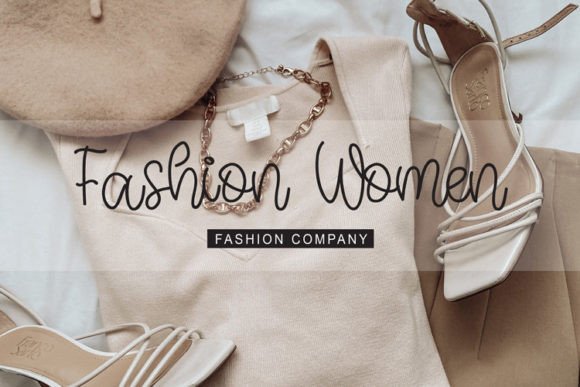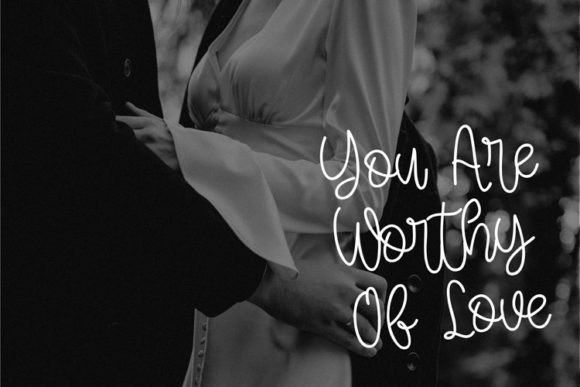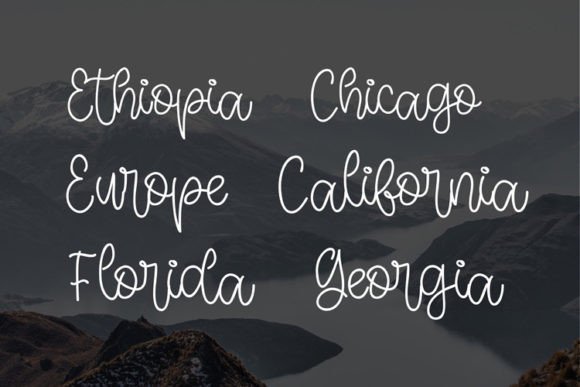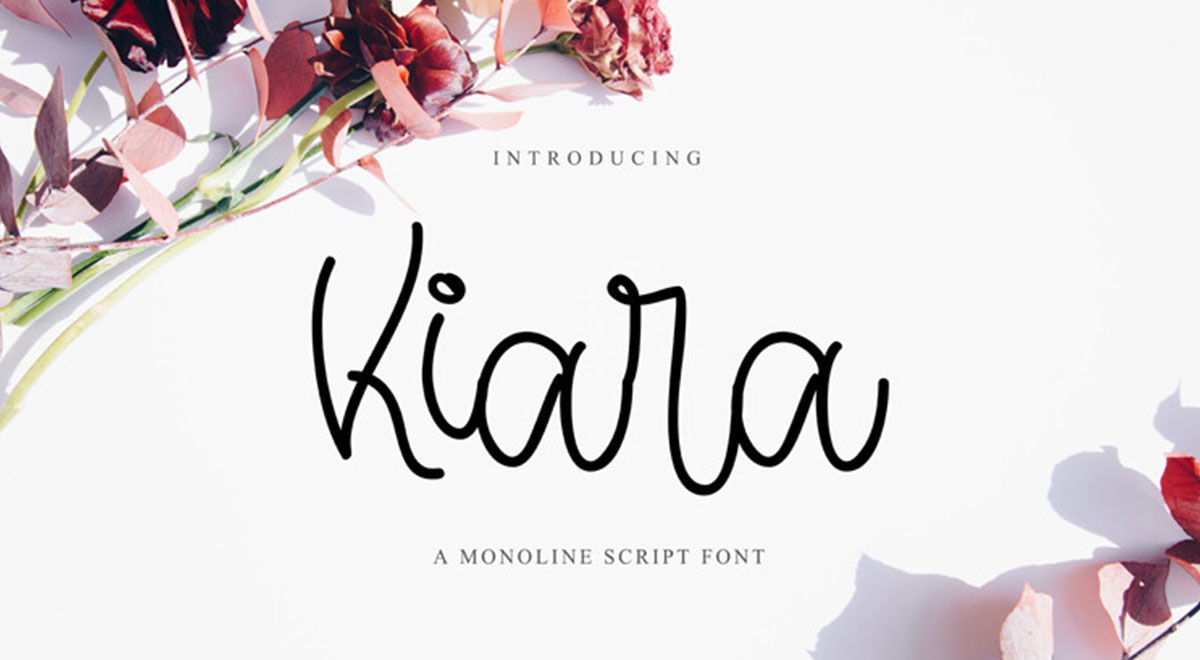
فونت Kiara انگلیسی
| ⭐ توضیحات | فونت کیارا را معرفی میکنیم، خطی برازنده و دلربا و دستنویسی که ظرافت و زیبایی را میتاباند. این فونت با خطوط روان و منحنی های ظریف خود، حسی از پیچیدگی را به طرح های شما می بخشد. فونت کیارا که برای دعوت عروسی، لوگوها و پروژههای برندسازی ایدهآل است، جلوهای از جذابیت جاودانه را میافزاید و ماهیت لطف دستنویس را با هر ضربه به تصویر میکشد. |